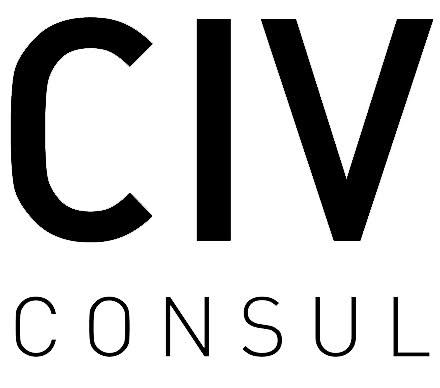
Welche Schriften sind in diesem Logo?
Welche beiden Schriften verwendet dieses Logo?
Wobei das auch hier die "FF DIN" sein müsste, erkennbar am ganz leichten Bogen beim C.